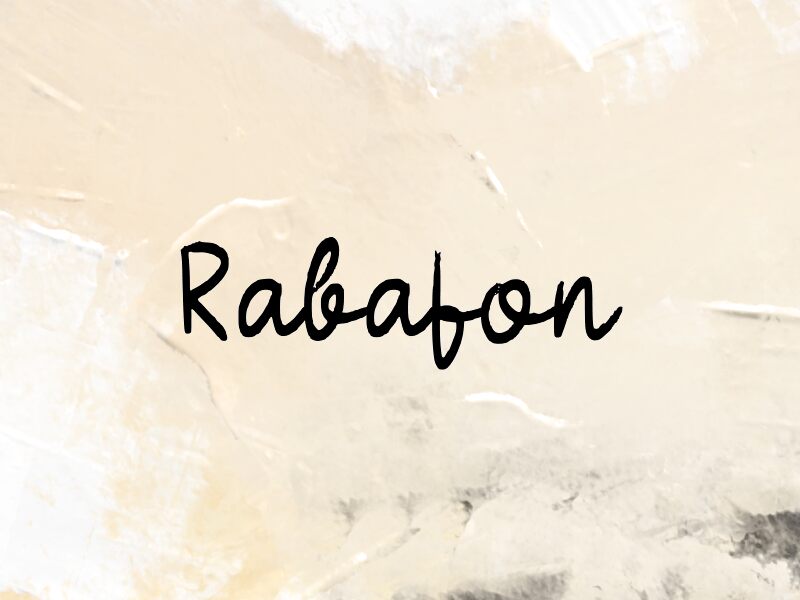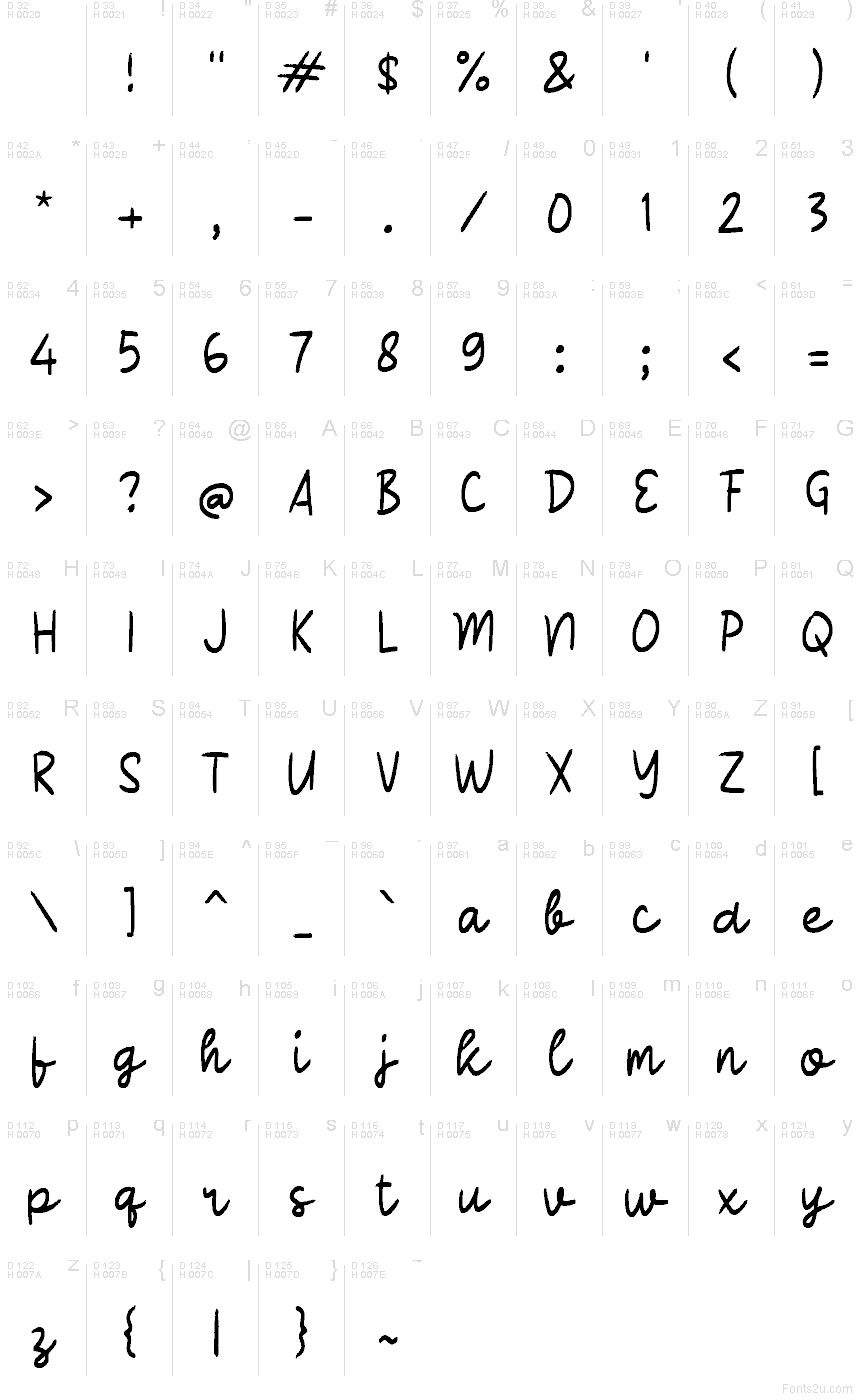
Rabafon
Rabafon от wep - это бесплатный рукописный шрифт, созданный в свободной манере письма маркером, где высокие петли чередуются с быстрыми, открытыми штрихами. Эта неравномерность придает буквам непринужденный и личный характер, а длинные перекладины и глубокие нижние выносные элементы создают эффект живого карандашного наброска.
Благодаря своей открытой и легкой структуре Rabafon идеально подходит для оформления меню в кафе, обложек блокнотов, поздравительных открыток, публикаций в соцсетях и лаконичной упаковки товаров. Шрифт также отлично дополнит вывески для мероприятий или крафтовые бирки, особенно там, где рукописная текстура выглядит уместнее, чем выверенная каллиграфия.